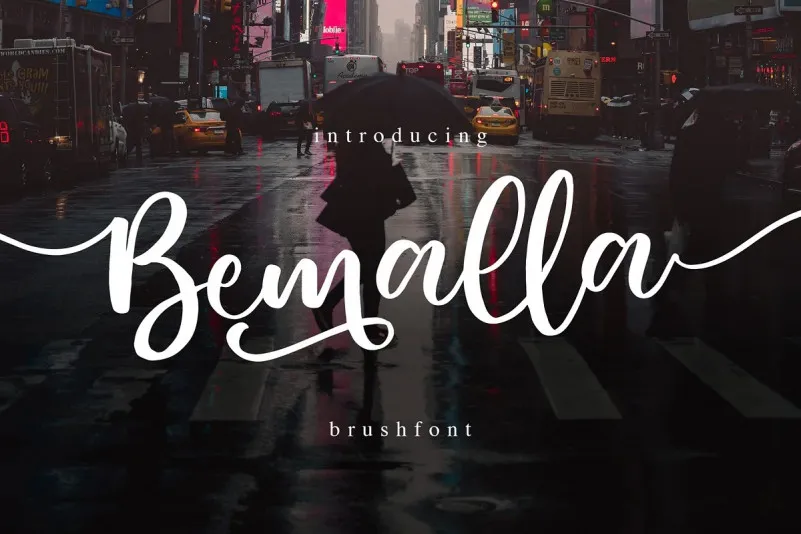
Bemalla Font – Download Grátis
A Bemalla Font é perfeitamente adaptada para quem busca uma paleta de cores natural na sua próxima criação gráfica. Esse script font foi especialmente projetado para adicionar um toque elegante aos seus trabalhos, garantindo resultados incrivelmente perfeitos e impecáveis. Quando combinada com conceitos de design da era Now que usam tons naturais como castanha e verde seco, a Bemalla traz uma beleza inatacável ao seu trabalho. Este é um resource font ideal para designers em busca de uma mistura única entre elegância e naturalidade. Suas linhas finas, sutilezas e detalhes delicados criam um aspecto sofisticado que ajuda a destacar o design do seu projeto. A Bemalla não apenas dá vida ao texto, mas também à sua narrativa visual, tornando-a uma escolha inteligente para qualquer projeto gráfico em busca de um toque especial e natural.